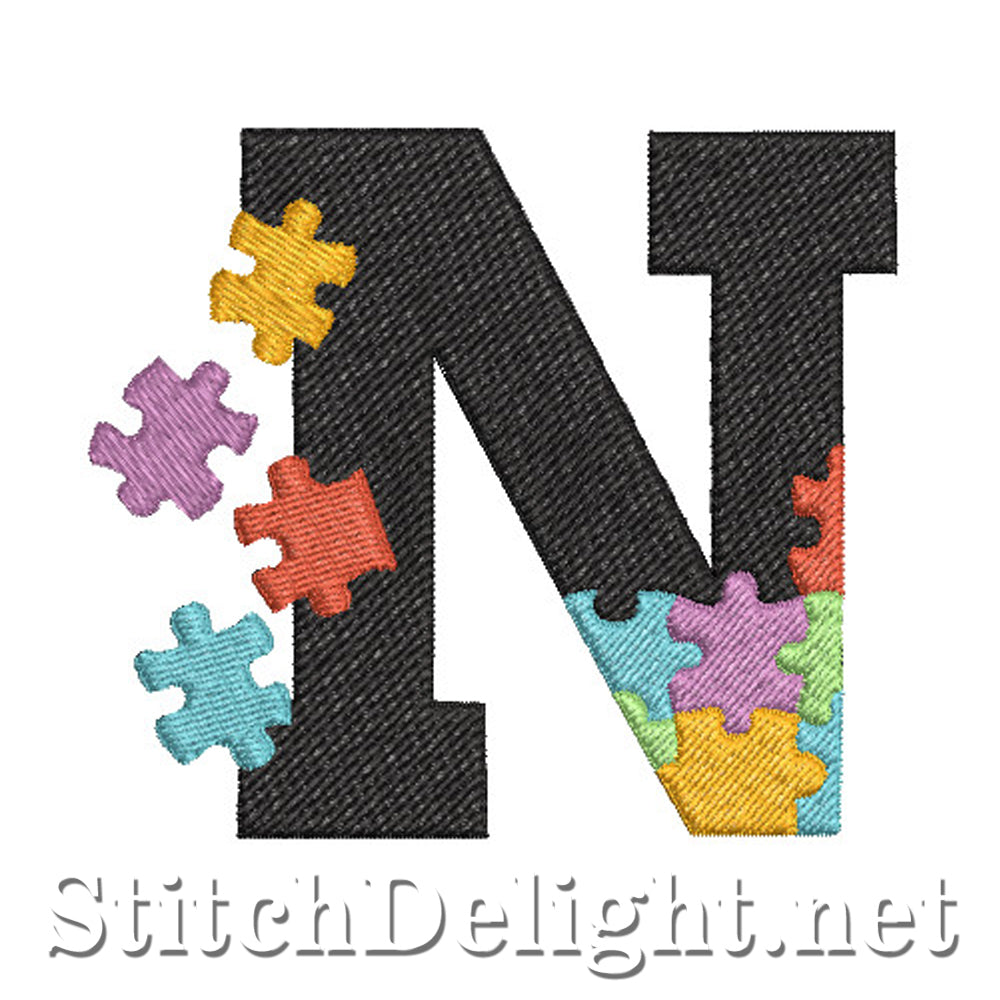
Police de puzzle SDS1522 N
Police colorée pour le cerceau 4x4, parfaite pour les projets pour enfants, les sacs de jeu et même les projets sur l'autisme. Il ne s'agit que des lettres majuscules avec la lune - le matelassage de fond et les petites lettres ne sont pas inclus dans cet ensemble mais peuvent être achetés séparément dans la section des polices.